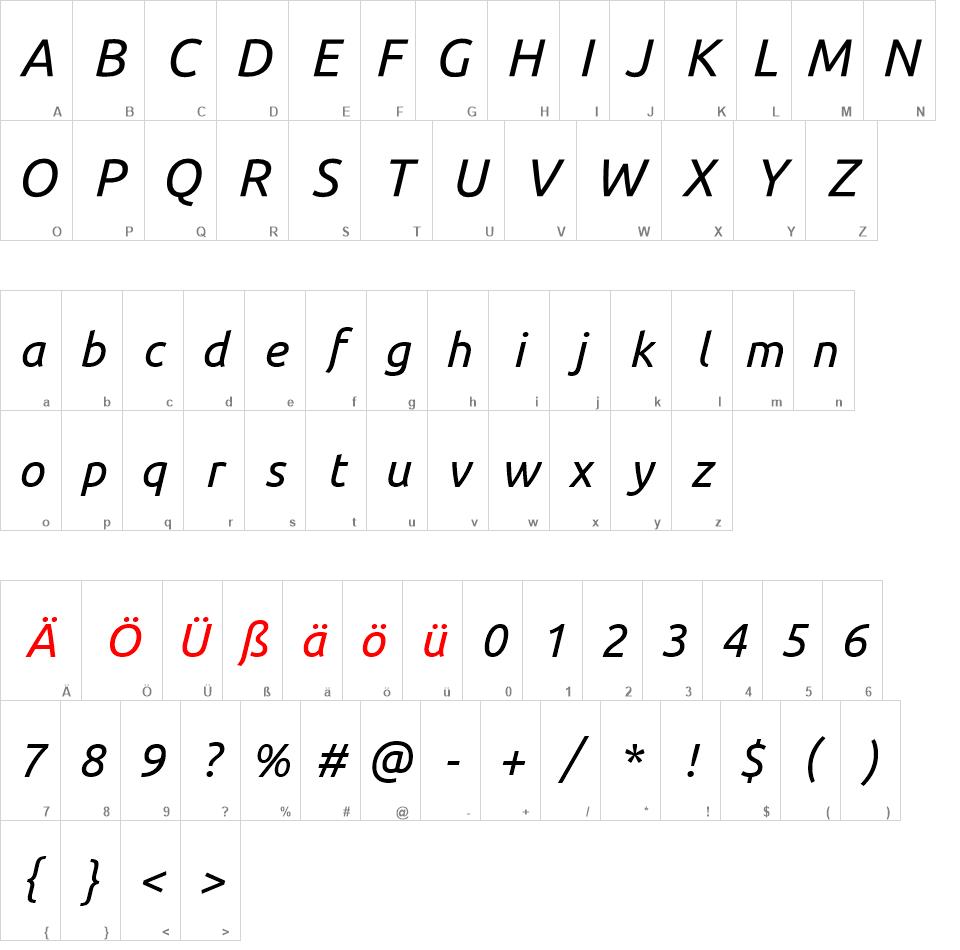
Ubuntu
Ubuntu  font
Die Ubuntu-Schriftfamilie besteht aus einer Gruppe von Sets, die mit den neuen Libre / Light-Schriftarten übereinstimmen. Die Entwicklung wird von der breiteren Free-Software-Community und Kanonik im Auftrag des Ubuntu-Projekts finanziert. Technische Studien zum Zeichensatzdesign und deren Implementierung werden von Dalton Maag durchgeführt.
TrueType / OpenType-Dateien und Designdateien, die zur Erstellung der Schriftfamilie verwendet werden, werden unter der offenen Lizenz verteilt. Die Designdateien werden ausdrücklich zum Testen, Ändern, Freigeben und Entwickeln vorgeschlagen. Die Schriftart ist serifenlos, verwendet OpenType-Funktionen und wird durch Klarheit auf Desktop- und mobilen Computerbildschirmen angezeigt.